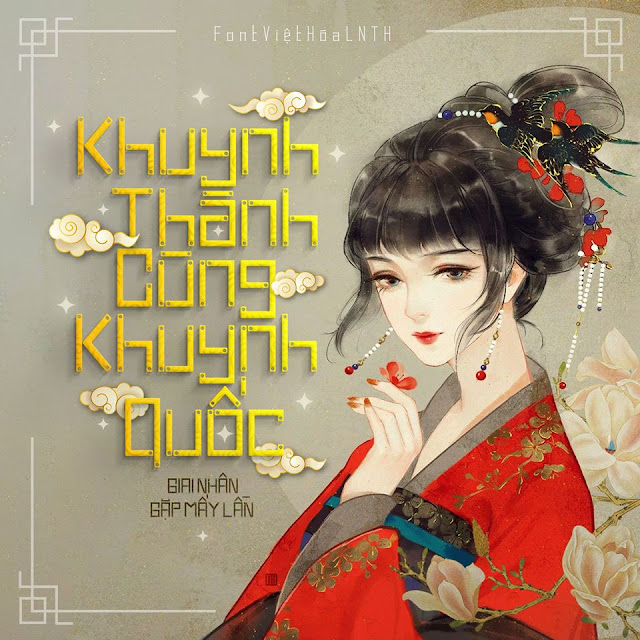
Font việt hóa LNTH Cross Screw
Font việt hóa LNTH Cross Screw – Bộ font chữ thiết kế cơ khí độc đáo
Giới thiệu về Font việt hóa LNTH Cross Screw
Trong thế giới sáng tạo, việc tìm kiếm một Font Miễn Phí mang phong cách riêng biệt luôn là ưu tiên hàng đầu của các nhà thiết kế. Font việt hóa LNTH Cross Screw là một tác phẩm typography ấn tượng, lấy cảm hứng từ những chi tiết kỹ thuật và đầu vít cơ khí. Với các đường nét gãy gọn, mạnh mẽ và mô phỏng hình dáng dấu thập của ốc vít, bộ font này mang đến hơi thở công nghiệp đầy hiện đại. Phiên bản việt hóa giúp người dùng tại Việt Nam dễ dàng ứng dụng vào các dự án đồ họa mà không lo lỗi font hay thiếu dấu tiếng Việt đặc trưng.
Đặc điểm nổi bật của Font việt hóa LNTH Cross Screw
Phong cách thiết kế hình học
Font việt hóa LNTH Cross Screw sở hữu cấu trúc hình học cực kỳ chặt chẽ. Mỗi ký tự đều được tính toán tỉ mỉ để tạo ra sự cân đối giữa các nét thẳng và các điểm nhấn mô phỏng đầu vít. Điều này giúp bộ font trở nên vô cùng phù hợp cho các chủ đề về công nghệ, xây dựng hoặc cơ khí điện tử. Sự cá tính của nó giúp các tiêu đề (headline) trở nên thu hút và có chiều sâu hơn so với các phông chữ truyền thống.
Tính ứng dụng thực tiễn cao
Dù có thiết kế khá phá cách, Font việt hóa LNTH Cross Screw vẫn đảm bảo được khả năng đọc tốt trên nhiều nền tảng. Bạn có thể sử dụng font chữ này cho thiết kế logo, bìa sách kỹ thuật, poster phim hành động hoặc các giao diện trò chơi điện tử. Đặc biệt, đối với các bạn học sinh và sinh viên ngành mỹ thuật, đây là công cụ đắc lực để làm nổi bật các bài thuyết trình về chủ đề sáng tạo máy móc.
Kết luận và trải nghiệm Font việt hóa LNTH Cross Screw
Nếu bạn đang tìm kiếm một làn gió mới cho kho tư liệu của mình thì Font việt hóa LNTH Cross Screw chính là lựa chọn không thể bỏ qua.